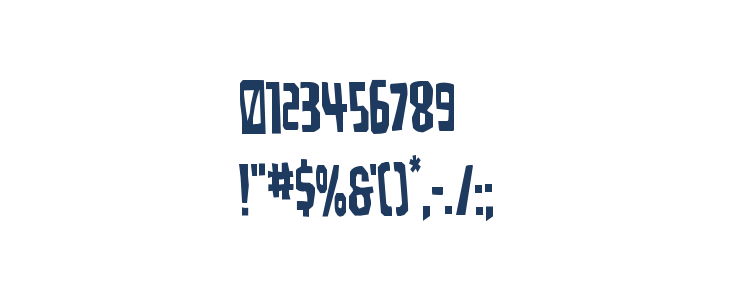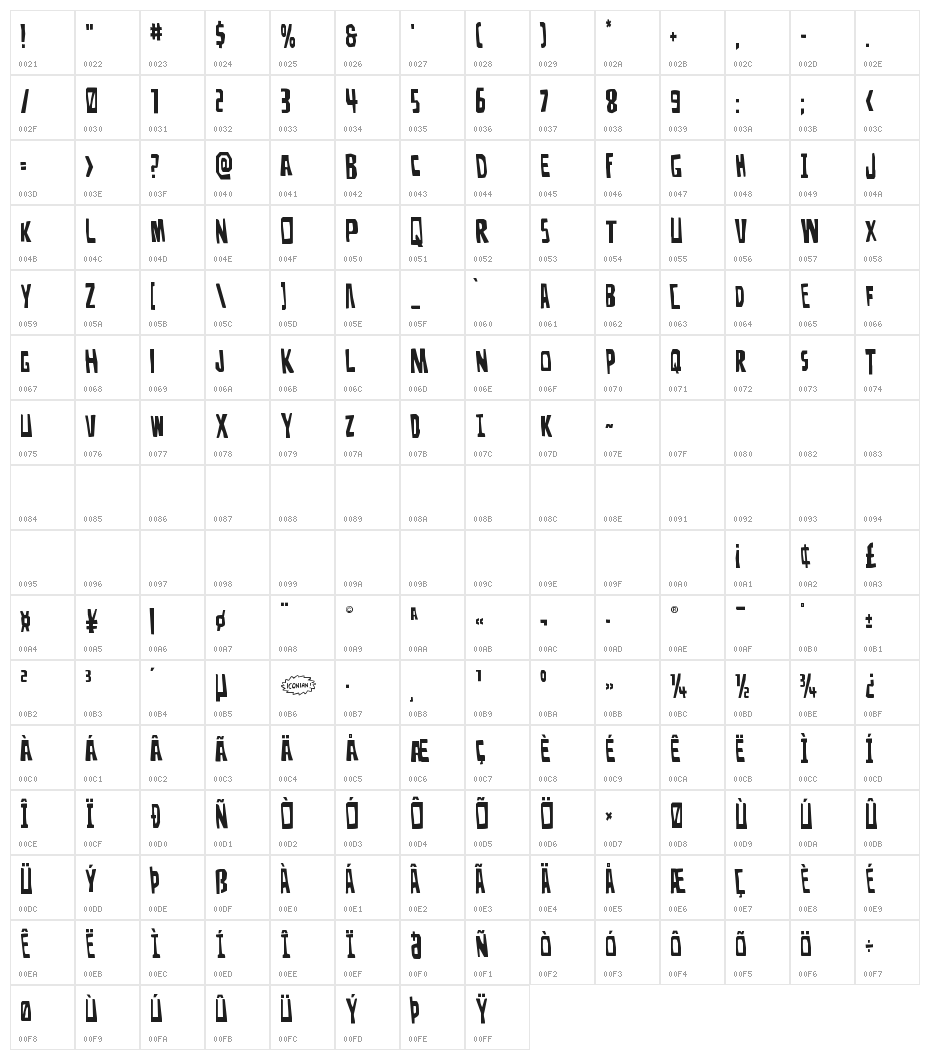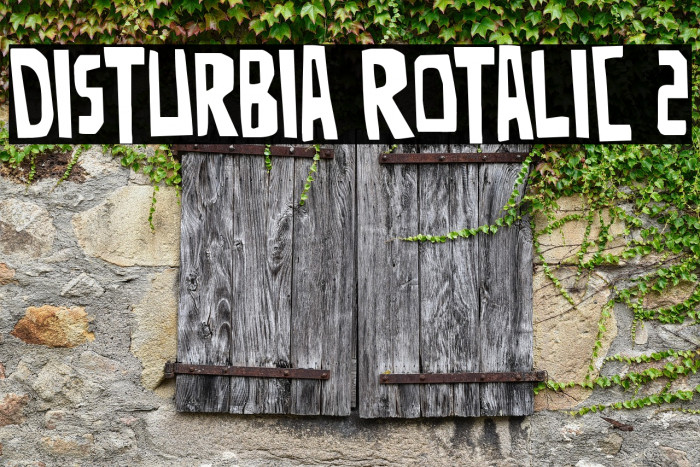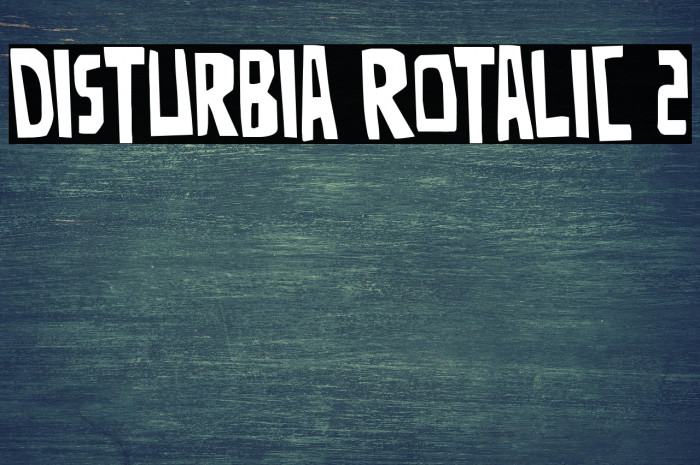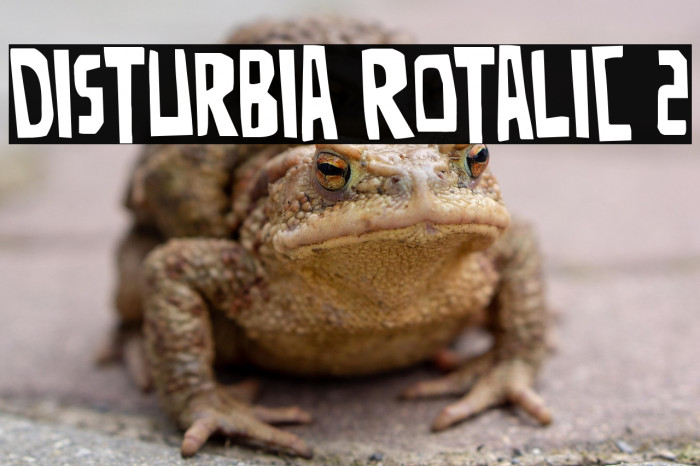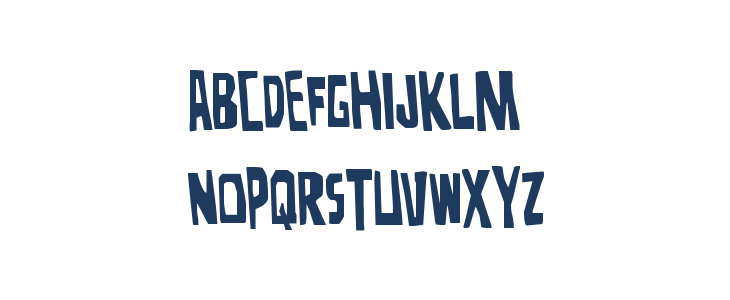
Disturbia Rotalic 2 Font
| Caso d'uso | Headlines, Posters, Logos |
| Progetti proposti | Ideal for music album covers, movie posters, or any design needing a bold, unconventional look. |